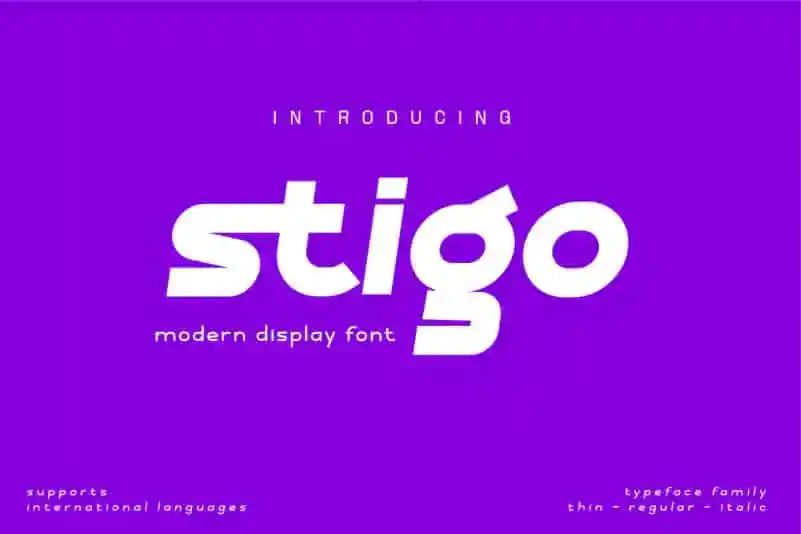
A Stigo Sans Serif é uma escolha perfeita para quem busca uma fonte moderna e elegante que se destaca na sua próxima criação visual. Essa fonte san-serif é simples e limpa, mas com um aspecto atraente e atemporal, especialmente nos detalhes cuidadosamente pensados nas curvas e grossuras dos caracteres. Com Stigo Sans Serif, você pode adicionar uma pitada de sofisticação e elegância a qualquer palavra ou frase que desejar, tornando seu design ainda mais poderoso e bonito. Esta fonte é perfeita para designers que valorizam um equilíbrio entre simplicidade e elegância, oferecendo um toque diferenciado em projetos de marca, logomarca, layout editorial ou qualquer outro projeto visual. Com uma atenção meticulosa aos detalhes em cada letra, Stigo Sans Serif é a escolha ideal para quem busca criar designs modernos e estilizados sem perder o brilho autêntico do tipo de texto.